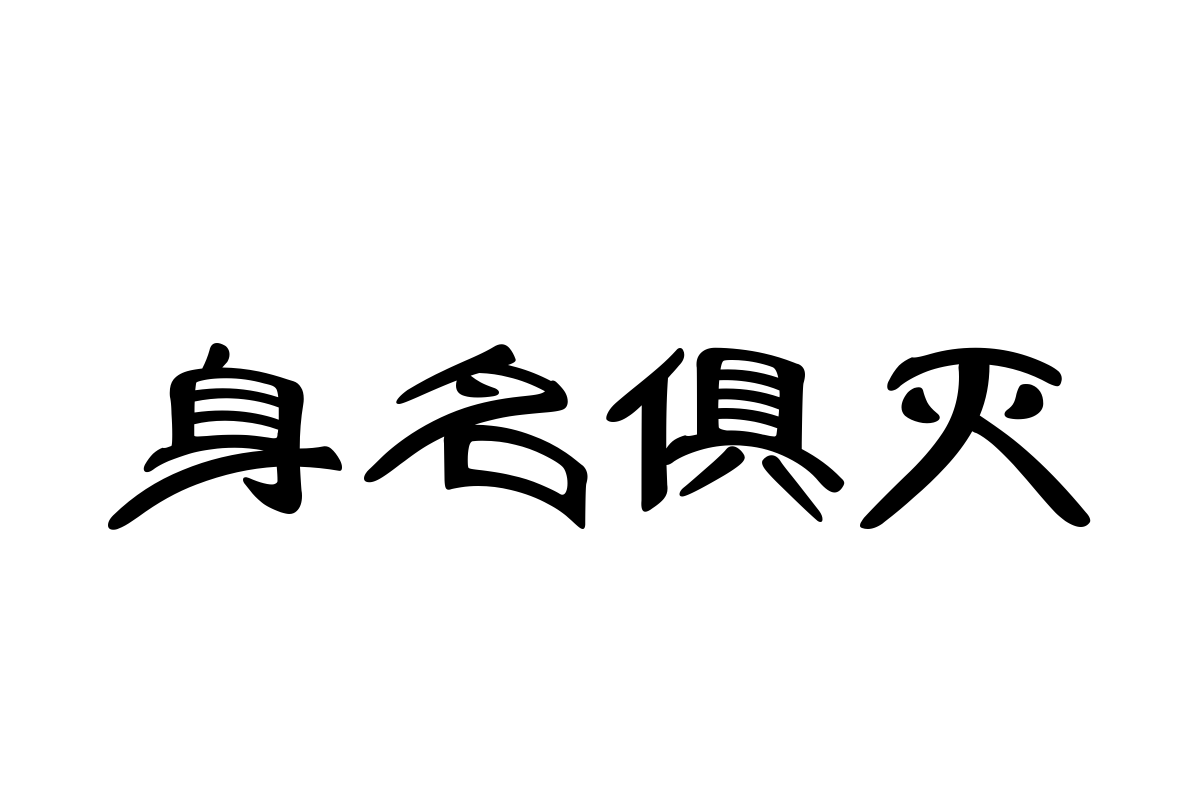
三极兜兜简体-Regular 字体是一款具有独特风格的中文简体字体,它以其独特的设计和风格吸引了许多设计师和用户的关注。该字体由三极公司设计制作,具有多种字形、笔画和结构特点,适用于各种应用场景。
三极兜兜简体-Regular 字体的特点如下:
1. 字形多样:该字体具有多种字形,包括楷书、行书、草书等,满足了不同用户的需求。
2. 笔画流畅:该字体的笔画流畅自然,给人一种优雅的感觉。
3. 结构紧凑:该字体的结构紧凑,使得整个字体看起来更加协调。
4. 易于阅读:由于其独特的设计和风格,三极兜兜简体-Regular 字体在阅读时更加舒适,不易产生视觉疲劳。
5. 适用范围广泛:该字体适用于各种应用场景,如网站、广告、海报等。
总之,三极兜兜简体-Regular 字体是一款具有独特风格的中文简体字体,它以其独特的设计和风格吸引了许多设计师和用户的关注。
三极兜兜简体-Regular